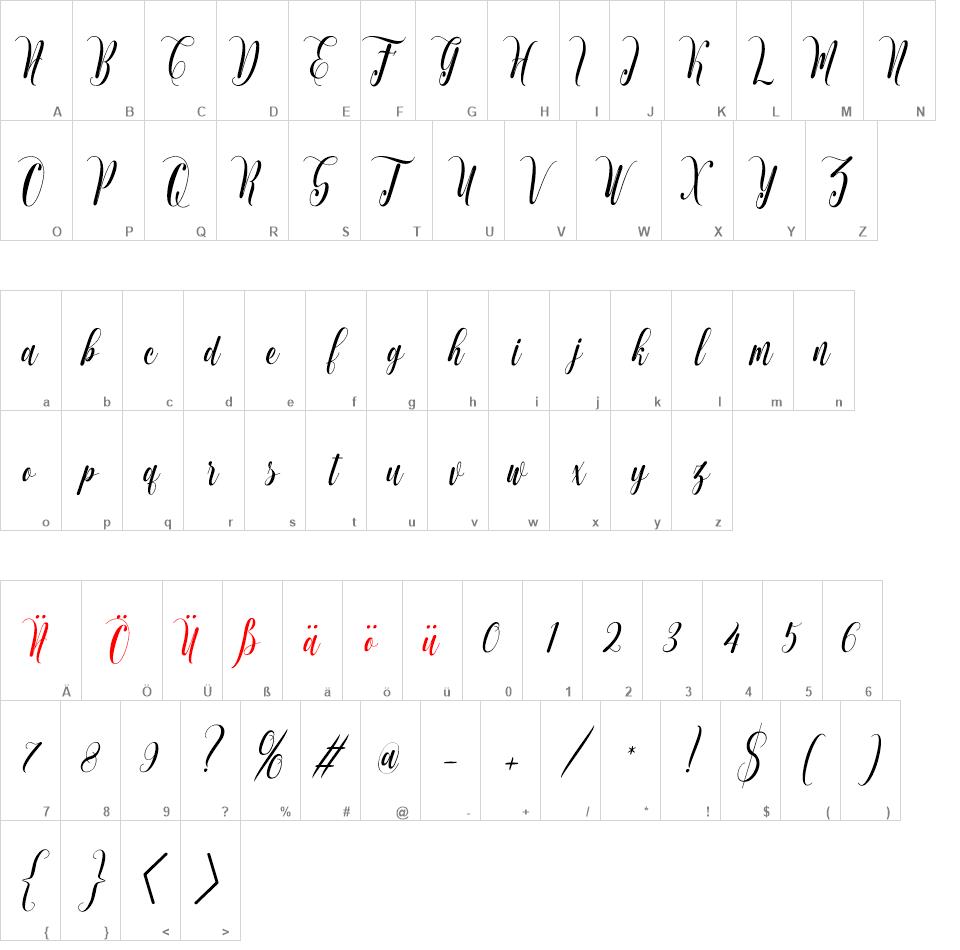
Muthya
Muthya ist ein Zeichensatz, der die Hand aufbaute, indem er den Charakter wie ein Tänzer auf und ab bewegte. Muthya hat einen sehr einzigartigen Kalligrafiestil